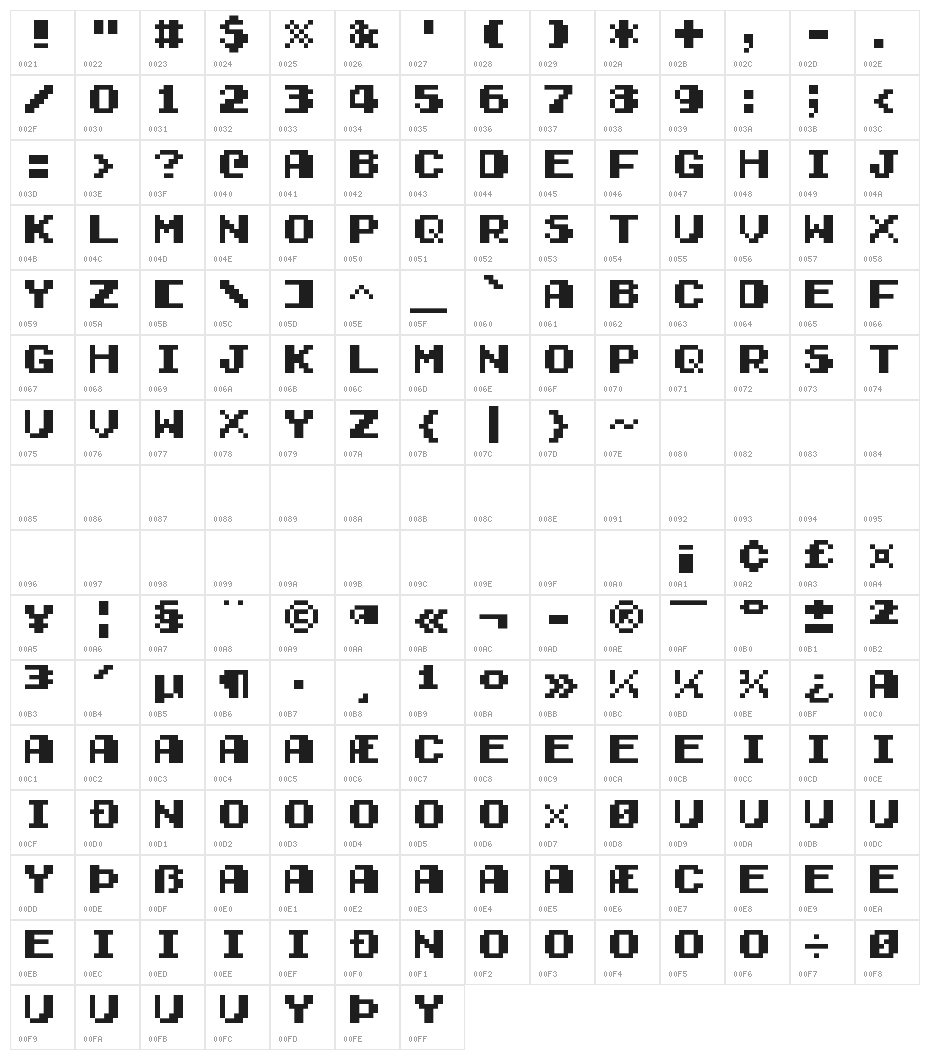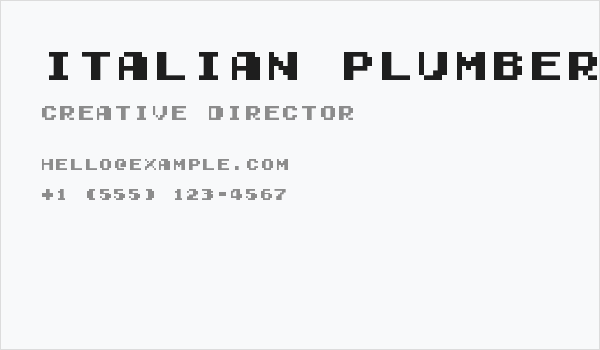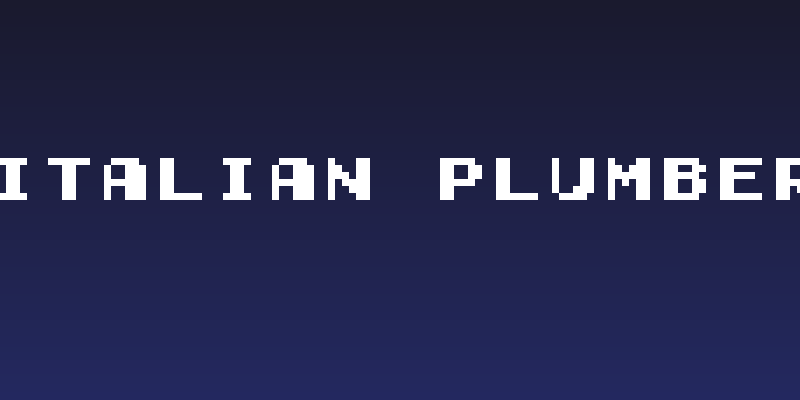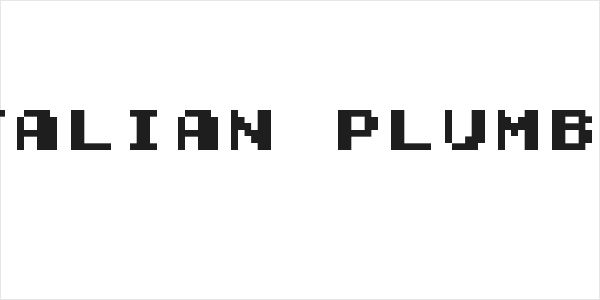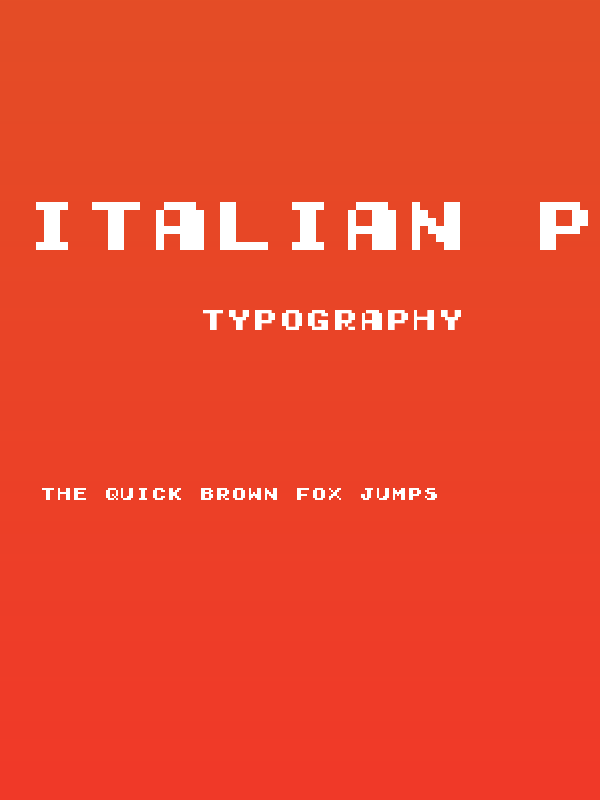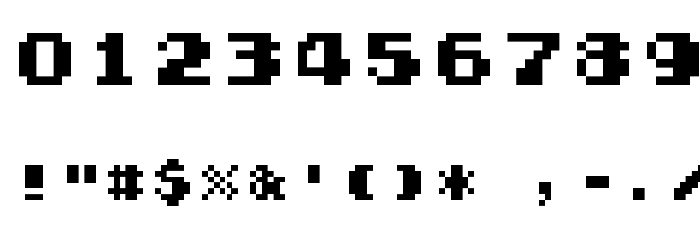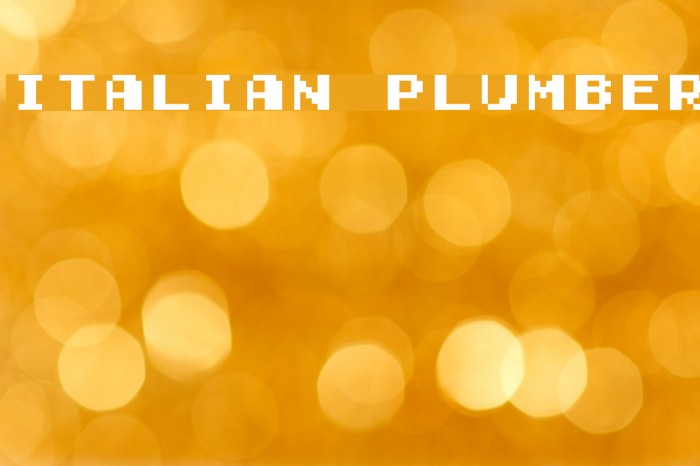
Italian Plumber Font
| الفئات | Pixel |
| النمط العام | Vintage |
| حالة الاستخدام | Logos, Headlines, Posters |
| مشاريع مقترحة | Ideal for video game design, retro-themed posters, digital art, and any project seeking a nostalgic or vintage digital look. |